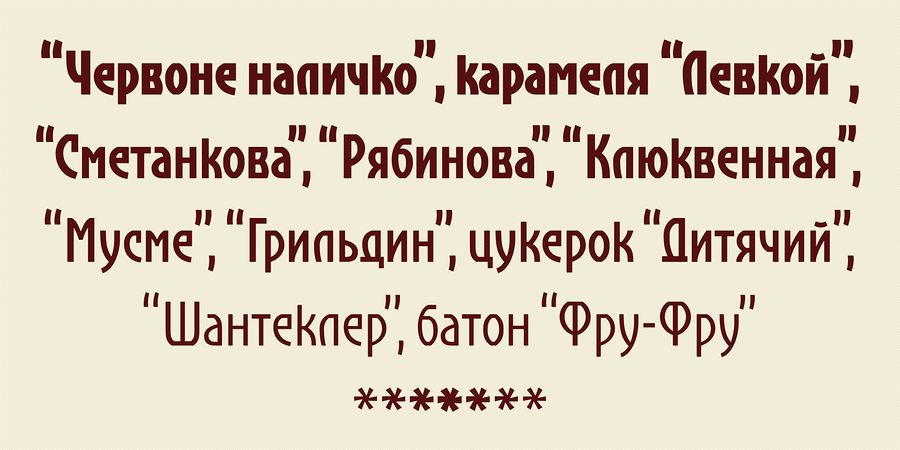
Konfekt (4 шрифта)
Основою цього шрифту стала реклама Київської кондитерської фабрики. Основне накреслення зробив Геннадій Заречнюк, після чого Віктор Харик розширив діапазон накреслень у ґарнітуру, що значно збільшило можливості використання. Стилістично шрифт несе всі ознаки ґротеску в стилі Модерн – зсунуті вгору і додолу оптичні вісі, викривлені дуги та прямі штрихи, примхливі та несподівані рішення окремих літер. Водночас його дещо геометризована ґротесковість дозволяє йому впевнено тримати рядок, а звужені пропорції та світліші накреслення чудово пасують для складання невеликих виділкових текстів для реклам, вивісок, часописів, меню, пакування тощо. Шрифт розробили Геннадій Заречнюк та Віктор Харик у 2019–2020 роках.
4 накреслення
Асоціації з сімейством шрифтів KonfektОсобистість і характер гарнітури:
стрункий, худий, художній, високий, консервативний, історичний, твердий, чіткий, ремісничий, крафтовий, гнучкий, гострий, кондовий, сильний, стабільний, стійкий, надійний, дерев'яний, важкий, залізний, яскравий, помітний, значний